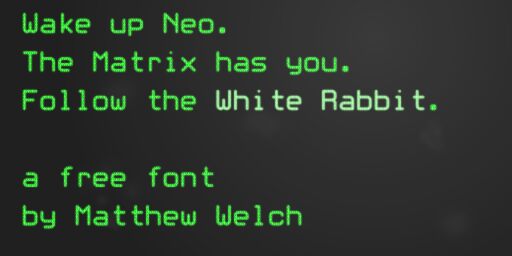
White Rabbit autorstwa Matthew Welcha to darmowy, zaokrąglony font techniczny typu display o miękkim, futurystycznym charakterze. Litery łączą w sobie prostotę monoline z zaokrąglonymi, „pigułkowymi” narożnikami i precyzyjnymi, kwadratowymi zwrotami, co nadaje krojowi przyjazny, elektroniczny wydźwięk, kojarzący się z grafiką interfejsów końca lat 90. oraz retro-futurystyczną stylistyką sci-fi.
Świetnie sprawdzi się w nagłówkach plakatów, okładkach albumów, menu gier, planszach tytułowych i opakowaniach, wszędzie tam, gdzie potrzebujesz eleganckiego, cyfrowego klimatu bez zbędnego chłodu. Jako darmowy font, White Rabbit idealnie nadaje się do krótkich haseł brandingowych i tekstów na okładkach – jego szerokie łuki i zwarte formy zapewniają zabawny, prosty i niepowtarzalny syntetyczny wygląd.